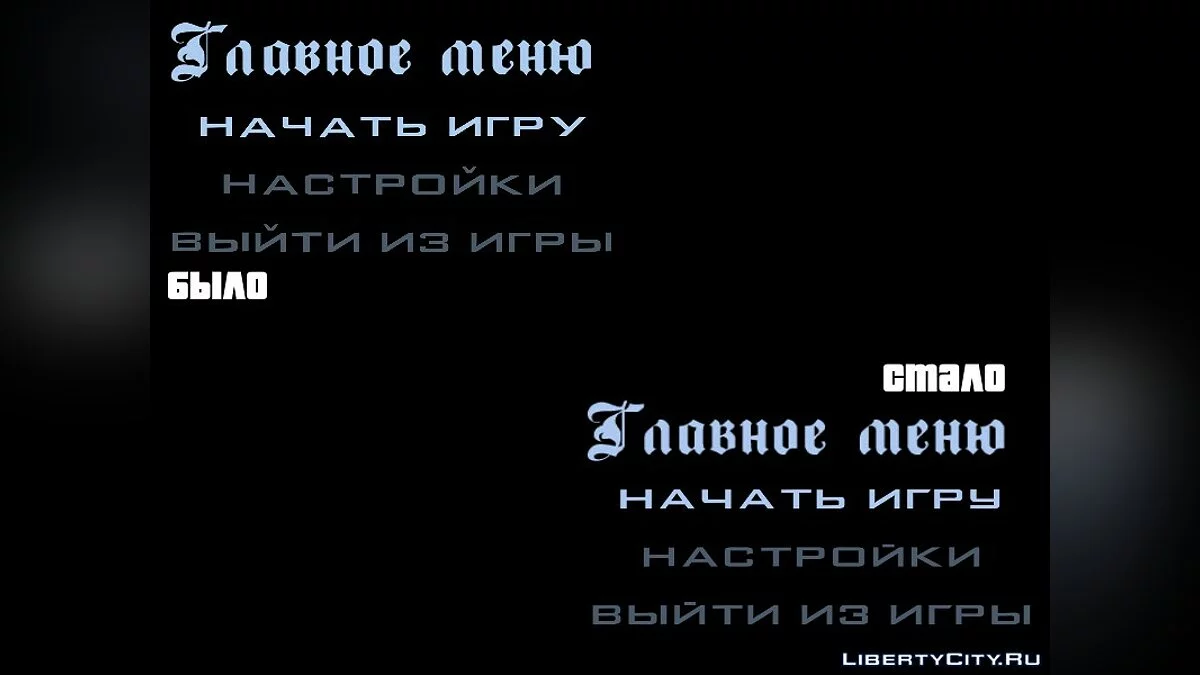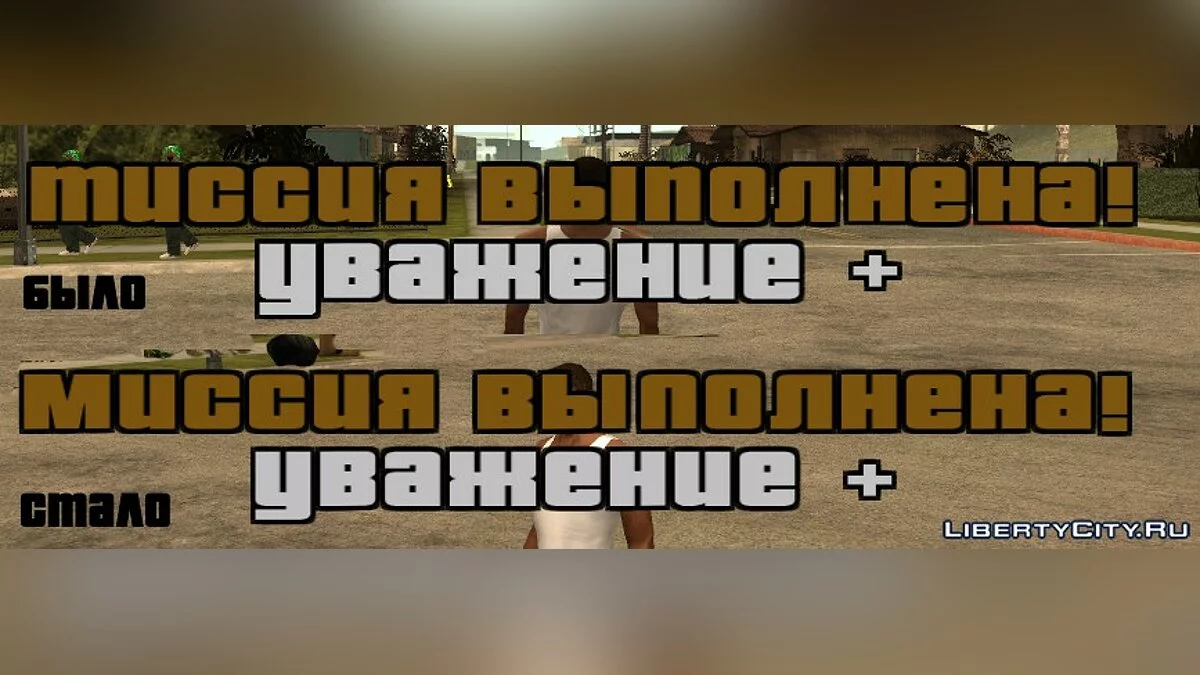
Обновленный нормальный шрифт для локализации от SanLtd
Когда-то давно (или не давно) DimZet, как и многие другие заметил, что дефолтный шрифт в русификаторе SanLtd вообще не похож на оригинальный, так что он сделал новый, похожий на оригинальный шрифт, но сделан он был слегка криво, так что я пофиксил его.
Изменения:
Шрифт Pricedown обновлен и взят из последней версии перевода.
Шрифты font2 не совпадали с font1 по разрешению, так что был взят шрифт разрешения 1024х1024 из последней версии перевода.